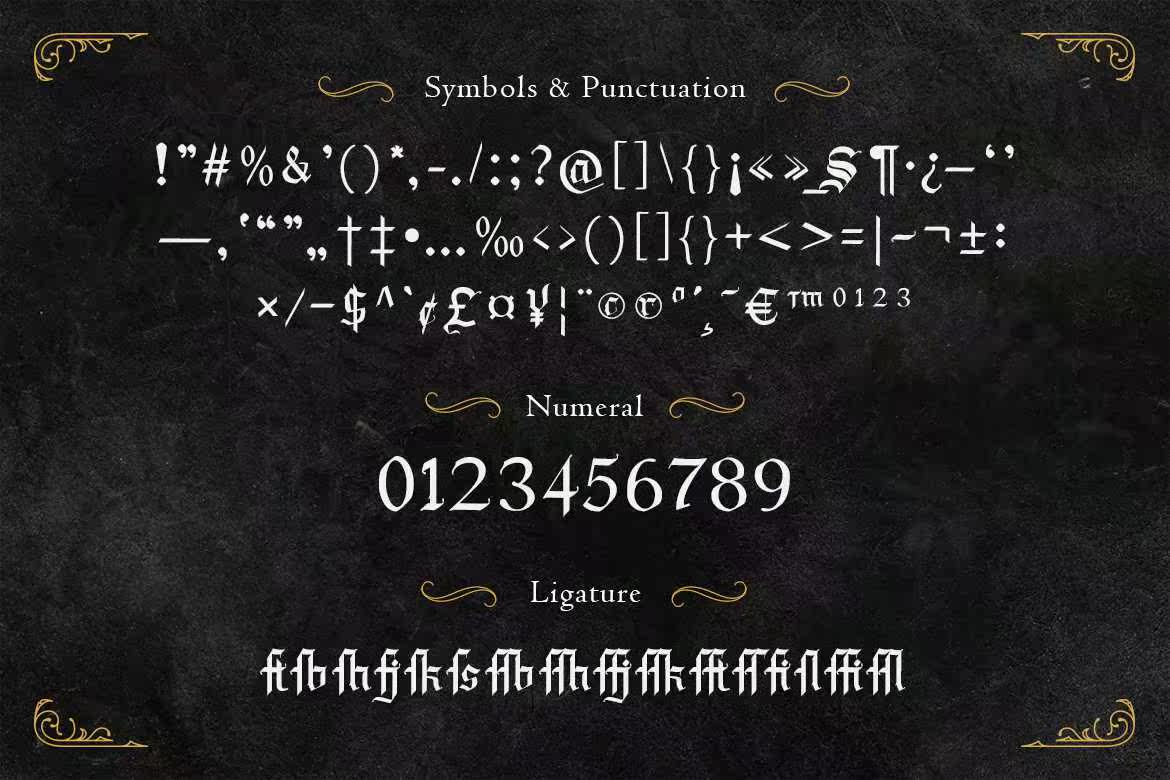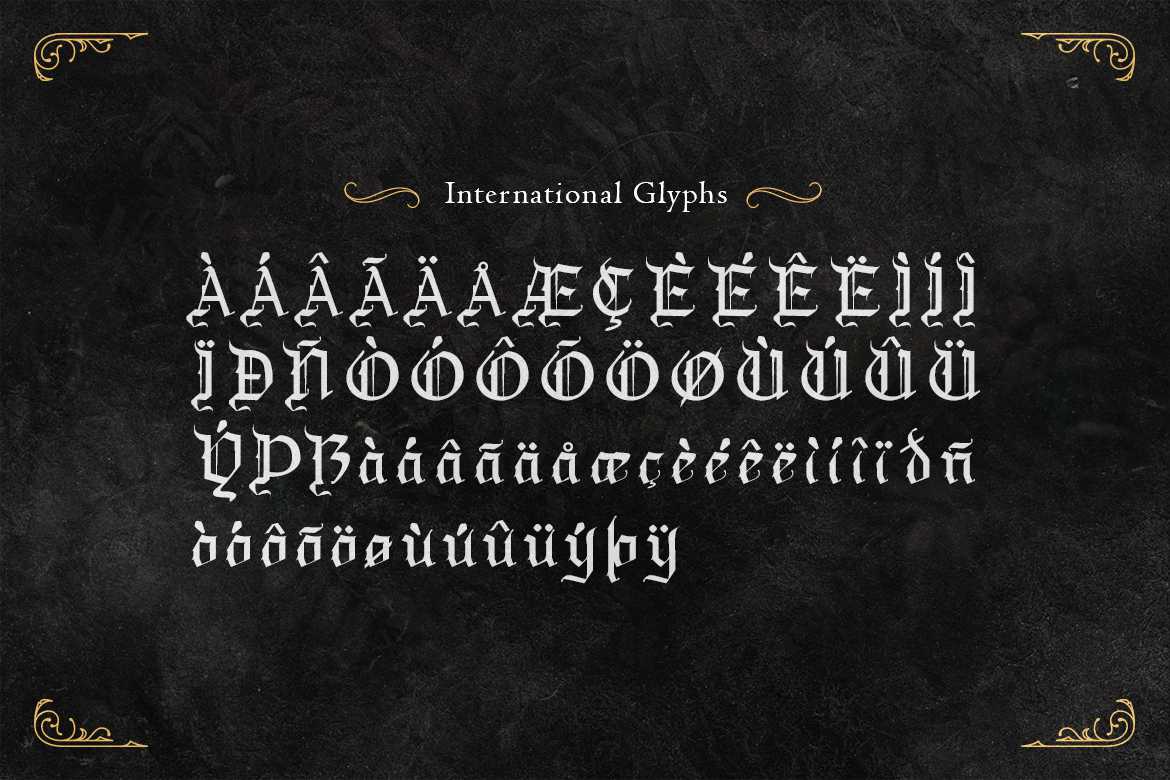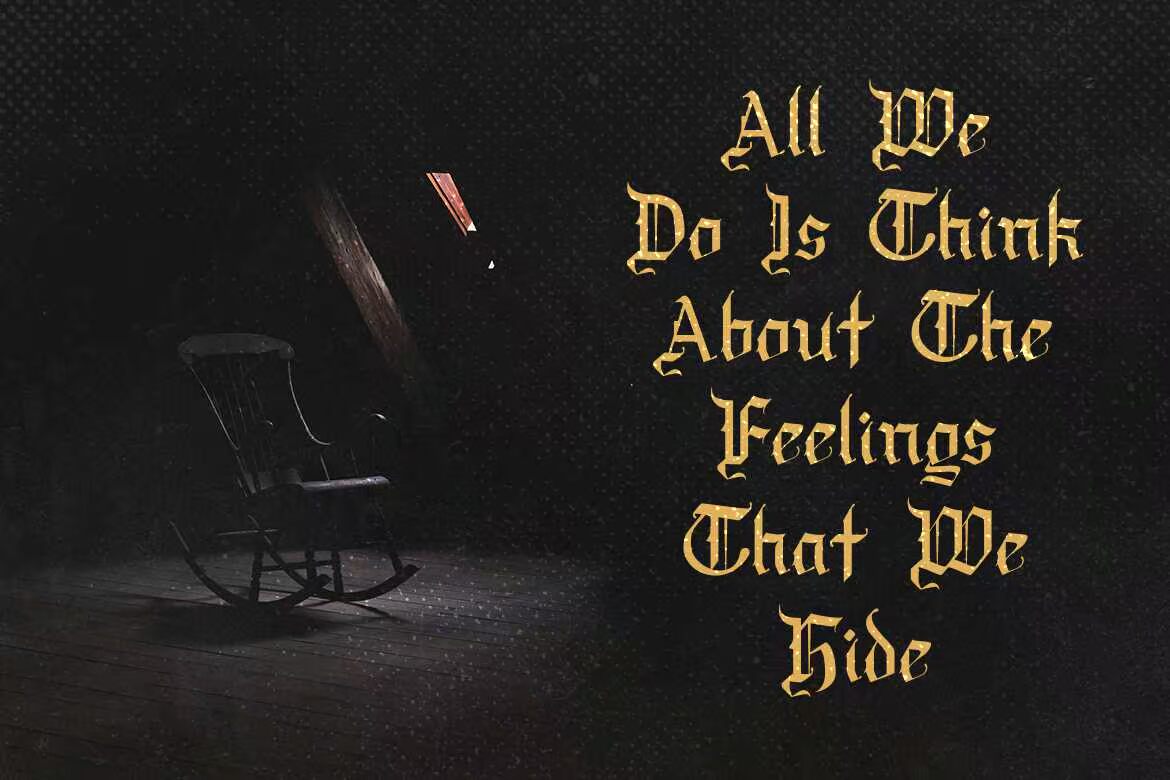
Draculieis Agothic Blackletter Font是一款适用于各种高风格木屋和深色建筑项目的绝佳选择。这种撕裂/撕裂风格的Blackletter Font在外观上非常适合您的设计。适用于服装、标签和包装、品牌或任何哥特式主题项目!Draculieis Agothic Blackletter Font是一款适用于各种高风格木屋和深色建筑项目的绝佳选择。这种撕裂/撕裂风格的Blackletter Font在外观上非常适合您的设计。适用于服装、标签和包装、品牌或任何哥特式主题项目!